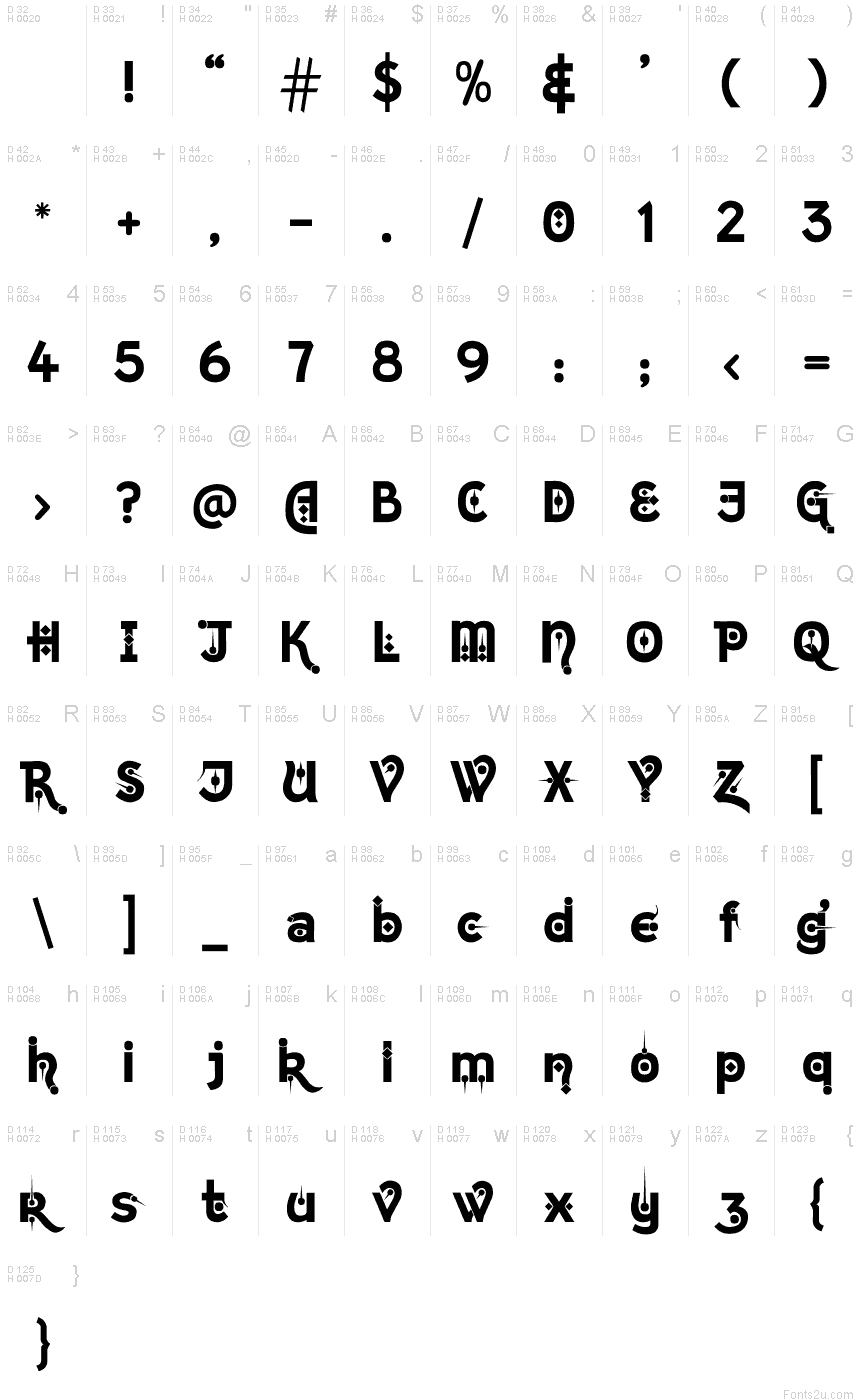
Kevin King 设计的 Kingthings Chimaera 是一款免费的装饰性展示字体,带有调皮且变幻莫测的个性。厚重的黑色笔画会出人意料地膨胀和收缩,而菱形点和钩状末端看起来就像是用光泽纸剪下来并拼贴在一起的一样。最终呈现出一种粗犷且富有质感的字体效果,半似卡通,半似怪兽,带着恰到好处的怪诞感,足以抓住眼球,又不失可读性。
使用 Kingthings Chimaera,您的标题和徽标会瞬间融入奇异的故事书世界——非常适合奇幻书籍封面、游戏图形、活动海报、万圣节促销、创意包装和非传统的品牌设计。这款免费字体在大字号下表现尤为出色,其厚实的曲线和锐利的点缀显得张力十足;在正文中,请搭配一款简洁的几何无衬线字体,以保持整体的易读性和稳重感。